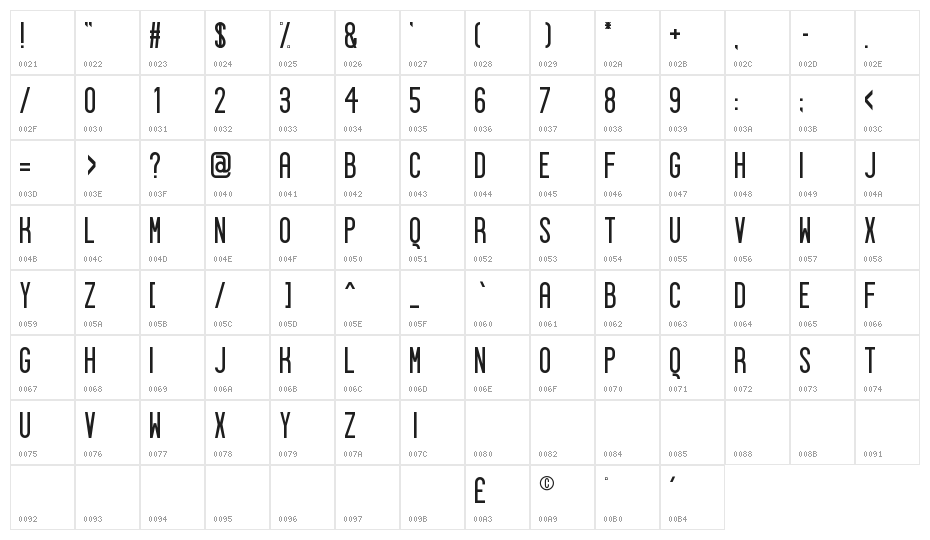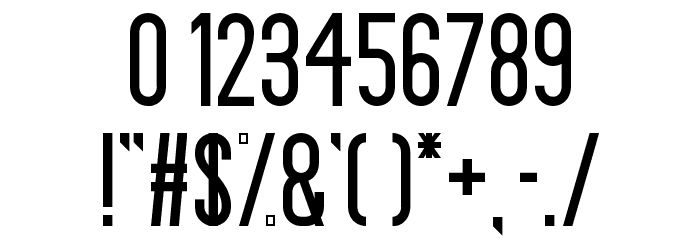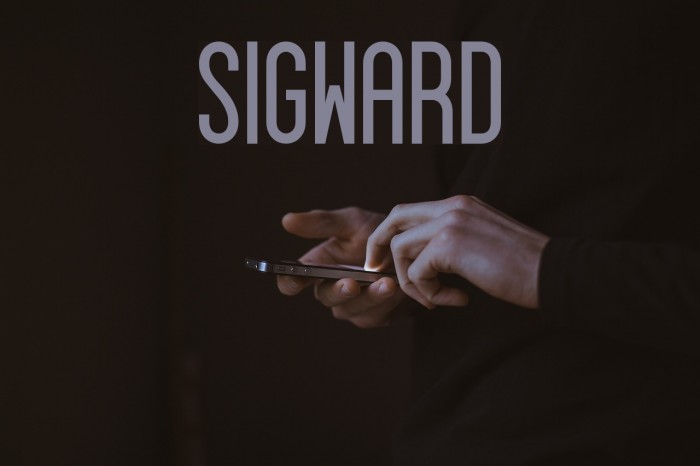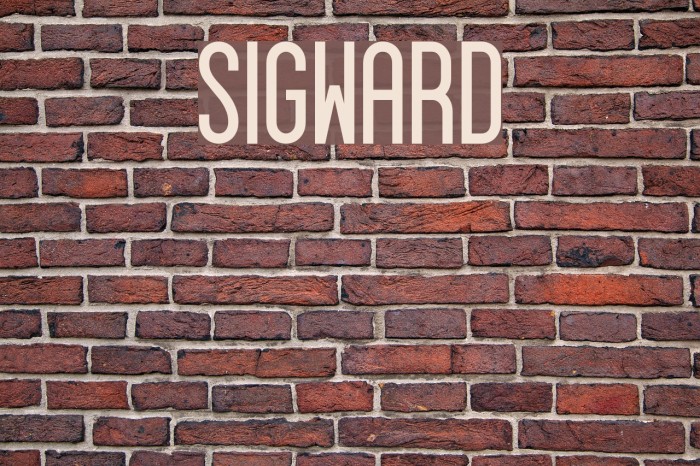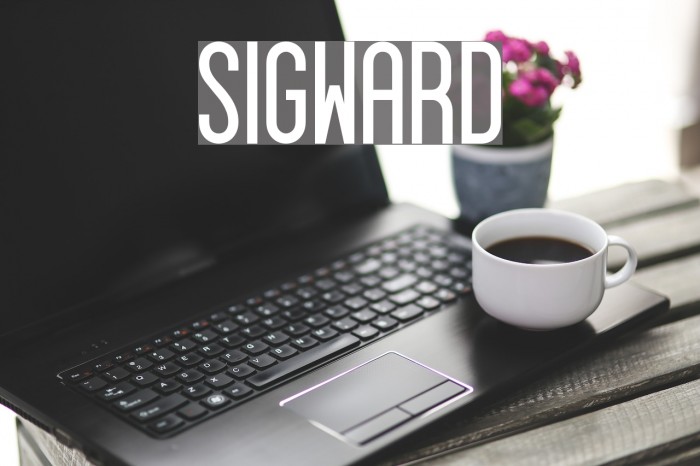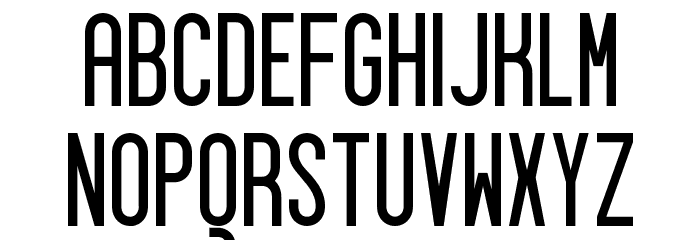
Sigward Font
✎ Sans Serif
| श्रेणियाँ | Sans Serif |
| चौड़ाई | Condensed |
| उपयोग का मामला | Headlines, Logos, Posters |
| सुझाए गए प्रोजेक्ट | Ideal for branding, advertising, posters, and web design where a modern and clean look is desired. |